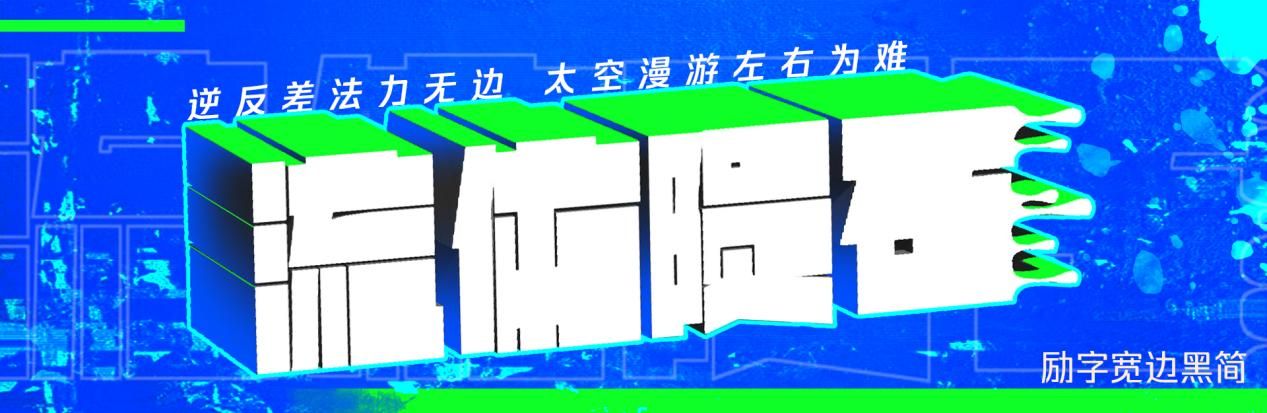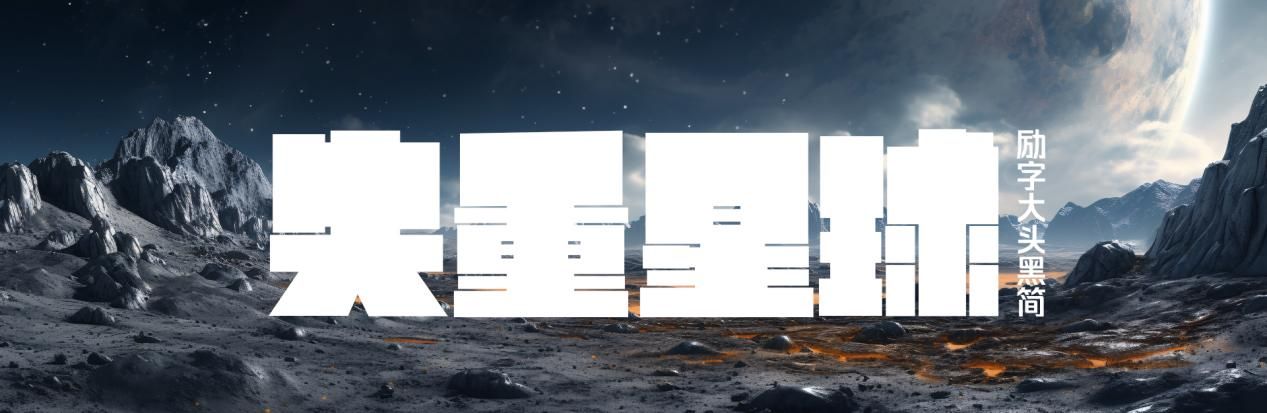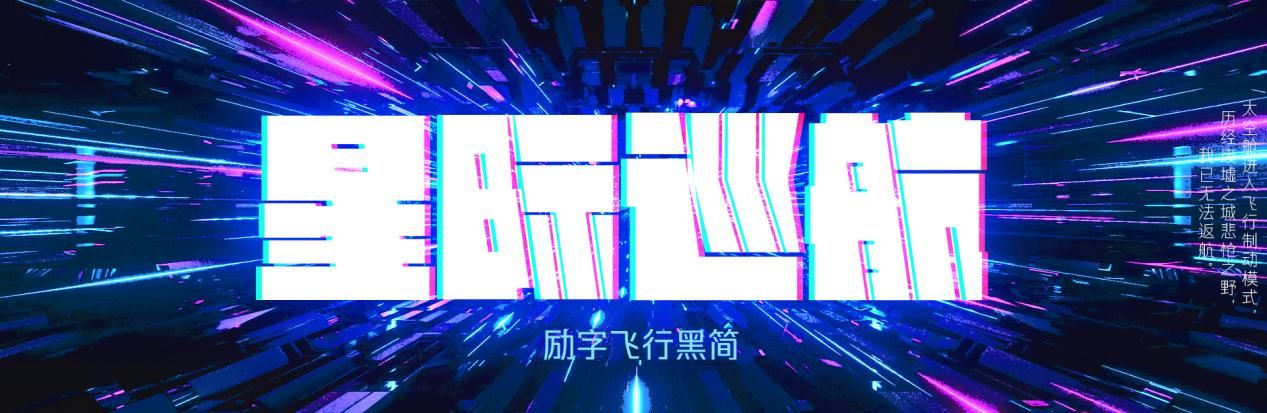
酷毙了!这套科幻风逆反差海报用起来也太炫了
体验过太空失重吗?
励字大头黑简字体内部重心失衡上移,笔画则打破传统规则,粗细组合不均,转折处以直角处理后,形成的一款横平竖直、右侧笔画厚重、左边笔画极细的逆反差直线字体。
体验过时空穿梭吗?
一款独特的变形字体——励字飞行黑简。字形方正、中宫宽博、起收笔平直,将左部字体重心向左倾斜,赋予字体独特的视觉张力,整体视觉形象模仿宇宙飞船的飞行状态。
体验过引力拉扯吗?
励字宽边黑简左侧字体紧密而右侧字体宽疏,字形方正规整,而重心随字体结构水平移动,以独特的字体组合方式,见证了流体星球的运转规则。